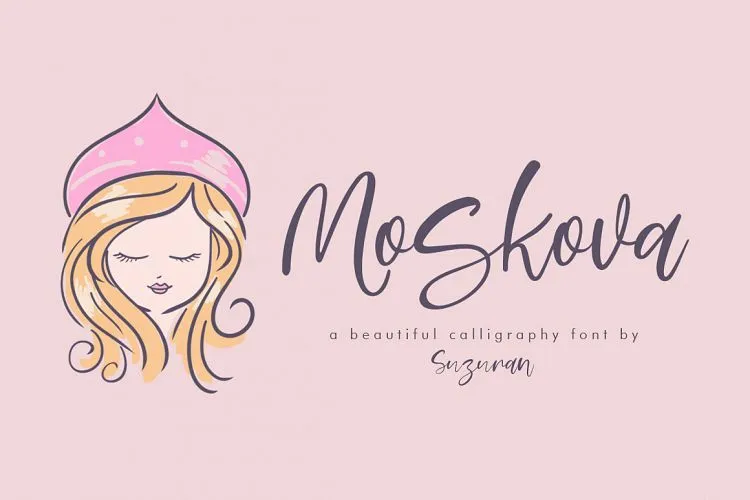
A Moskova Script é uma nova fonte de escrita calligrafia introduzida pela M.0Type, apresentando um estilo único e fresco. Ideal para criar identidades visuais como logotipos, etiquetas e selos, a Moskova se destaca por sua beleza única e originalidade, criada com mão. Além disso, vem com bonus, incluindo uma fonte Night in Kansas e Free Pen Script, tornando-a perfeita para um vasto range de aplicativos gráficos como logotipos, cartões de visita, panfletos, roupas, marcação, convites de casamento, adesivos, mensagens de linha, e design de layout. Seja você designer, marqueteiro ou webmaster, a Moskova Script vai transformar sua identidade visual em algo realmente único e memorável.